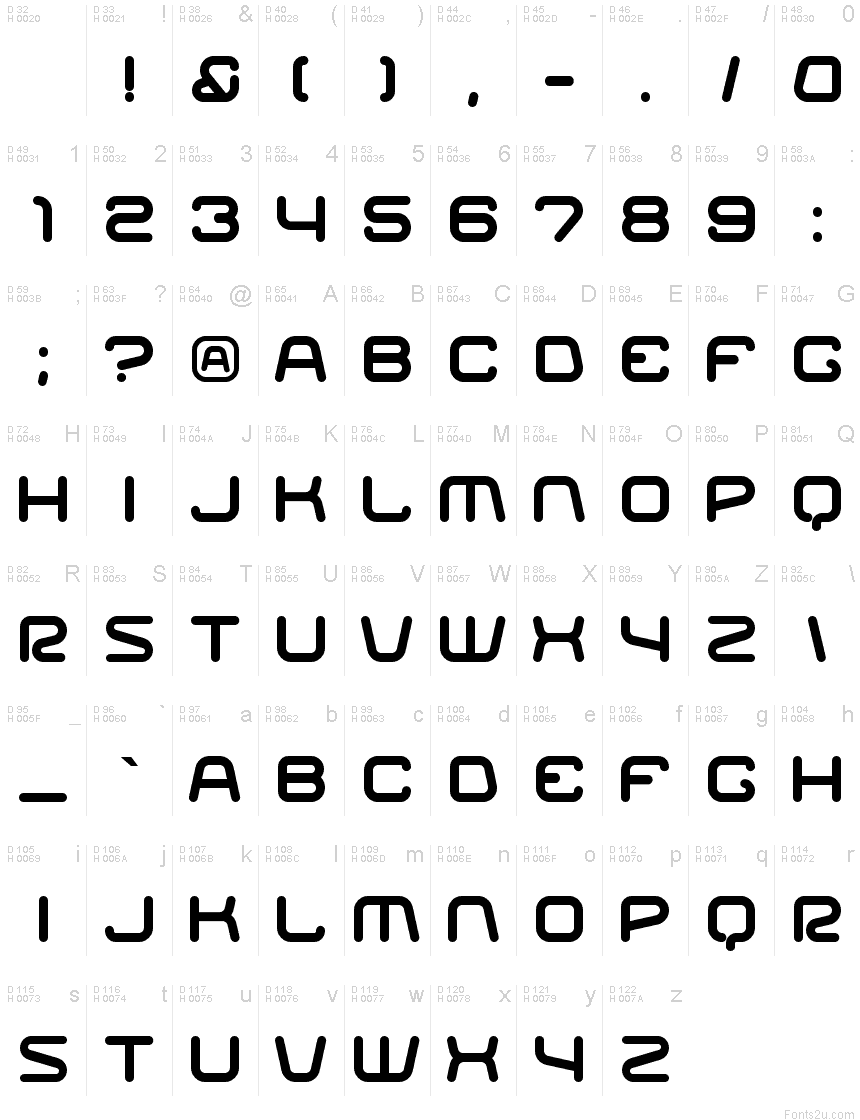
Racer od Onezero to darmowy, futurystyczny font typu display, który oddaje płynny, wyścigowy klimat technowej typografii z przełomu lat 90. i 2000. Wielkie litery są szerokie, zaokrąglone i precyzyjnie zaprojektowane, a przycięte łuki i poziome cięcia sprawiają, że alfabet wydaje się szybki, ale nie traci swojej łagodności.
Dzięki temu jest to naturalny wybór do tytułów gier, plakatów eventowych, identyfikacji wizualnej w sporcie, klubowych ulotek i okładek albumów – wszędzie tam, gdzie darmowy font potrzebuje ruchu bardziej niż nostalgii. Świetnie sprawdza się również w krótkich logotypach, planszach tytułowych i monogramach, ponieważ szerokie kształty i powtarzające się zaokrąglone narożniki sprawiają, że nawet krótkie słowa wyglądają spójnie i mechanicznie.